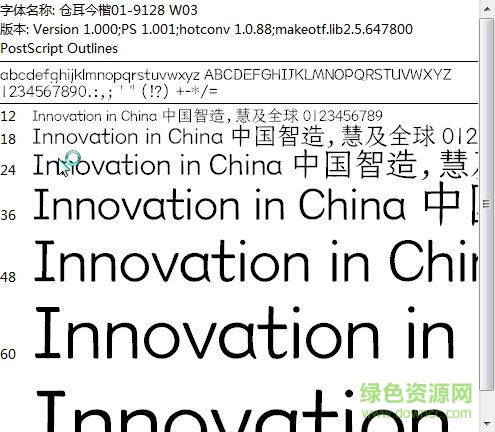
倉(cāng)耳今楷03字體是倉(cāng)耳今楷系列字體的第三款,類似于常規(guī)字體,有著常見(jiàn)的粗黑設(shè)計(jì)和舒適的視覺(jué)效果,歡迎大家來(lái)綠色資源網(wǎng)免費(fèi)下載!
倉(cāng)耳今楷01家族字庫(kù),設(shè)計(jì)師在筆形的設(shè)計(jì)上借鑒了中國(guó)傳統(tǒng)楷書,在字體結(jié)構(gòu)上,創(chuàng)造性的調(diào)整了筆畫的空間布局,讓字體在電子屏幕上的識(shí)別度更高,使讀者能夠從中得到更為舒適、愉悅的閱讀體驗(yàn)。
倉(cāng)耳今楷01這款字體共有五個(gè)字重,號(hào)稱“中國(guó)第一套楷體家族字庫(kù)”。說(shuō)來(lái)也是,目前面世的楷體都只有一種字重。
倉(cāng)耳字庫(kù)主創(chuàng)設(shè)計(jì)師嚴(yán)永亮,畢業(yè)于中央美術(shù)學(xué)院,曾師從王敏教授。工作室旨在為中國(guó)設(shè)計(jì)更多具有民族特色,引領(lǐng)時(shí)代審美的字庫(kù)。
中文閱讀的舒適性,是一個(gè)非常復(fù)雜的問(wèn)題。倉(cāng)耳今楷01,從筆形、布白、結(jié)體、排版四個(gè)方面進(jìn)行了深入研究,呈現(xiàn)出舒適的閱讀效果。
倉(cāng)耳今楷01有W01、W02、W03、W04、W05五個(gè)字重,可以滿足不同的應(yīng)用場(chǎng)景和媒介。
倉(cāng)耳今楷,布白相對(duì)均勻,使字體更具識(shí)別性。結(jié)合楷體筆形的特點(diǎn),比起黑體看的更為清晰。
倉(cāng)耳今楷筆形設(shè)計(jì)簡(jiǎn)潔,識(shí)讀更為輕松。倉(cāng)耳今楷,布白相對(duì)均勻,使字體更具識(shí)別性。結(jié)合楷體筆形的特點(diǎn),比起黑體看的更為清晰。